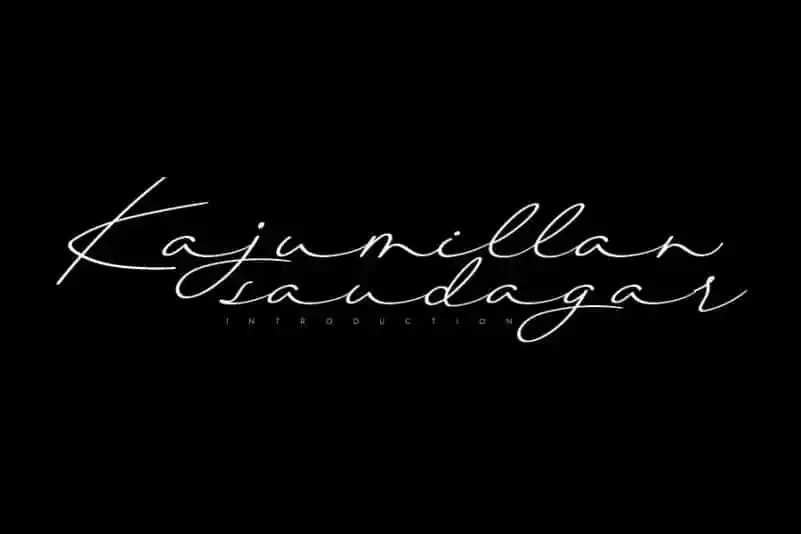
Kajumillan Handwritten Font é uma fonte de escrita manual com traços fluidos que capturam a elegância e sofisticação dos textos criados à mão livre. Esta fonte perfeita para projetos pessoais se destaca por sua aparência distintiva e sua estética clássica, oferecendo um toque romântico e emotivo ao seu design. Não importa qual projeto você esteja desenvolvendo, Kajumillan Handwritten Font o ajudará a criar designs impressionantes que capturam os sentimentos mais apaixonados e únicos. Seu estilo único é tão singular quanto eterno, tornando-se uma escolha ideal para designers, gráficos digitais ou criativos de todos os tipos. Experimente Kajumillan Handwritten Font e descubra como ele pode fazer seu trabalho soar ainda mais especial.